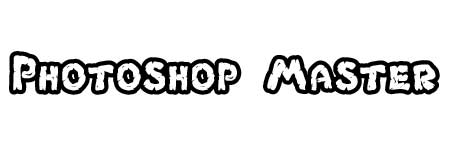
Да, отличный шрифт!!!
черепашки ниндзя епть
Отлично! Как раз то что надо!
Прикольный шрифт!
Таки никто не узнаёт, что этот шрифт из первого, классического мультсериала о черепашках ниндзя? Ну дела...
Отличный шрифт!)
отлично)))
шрифт супер!)
=) класс
АфФигеть!!!